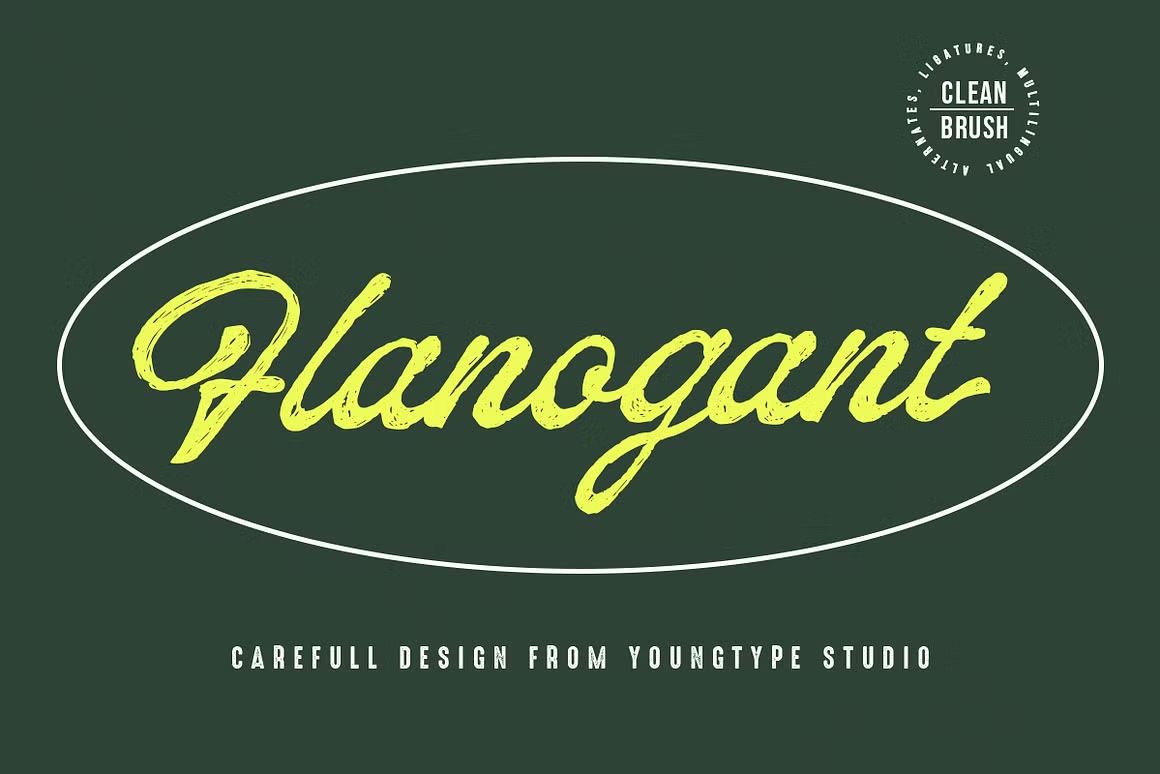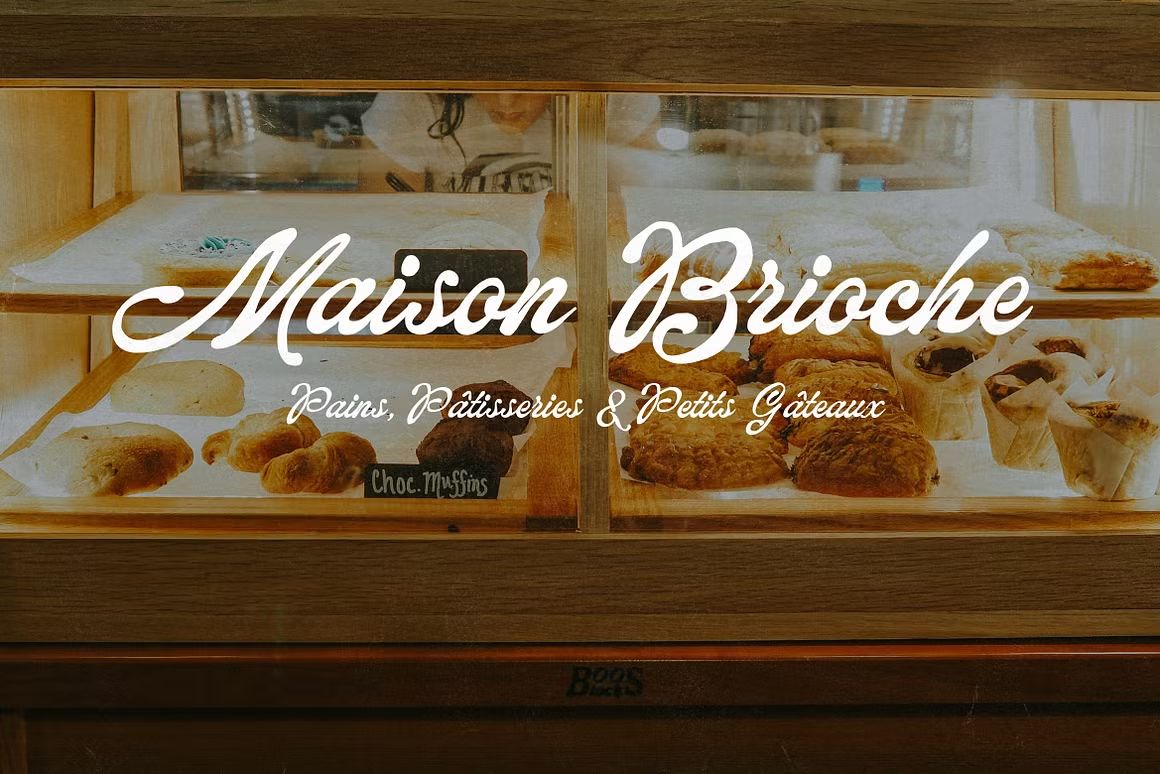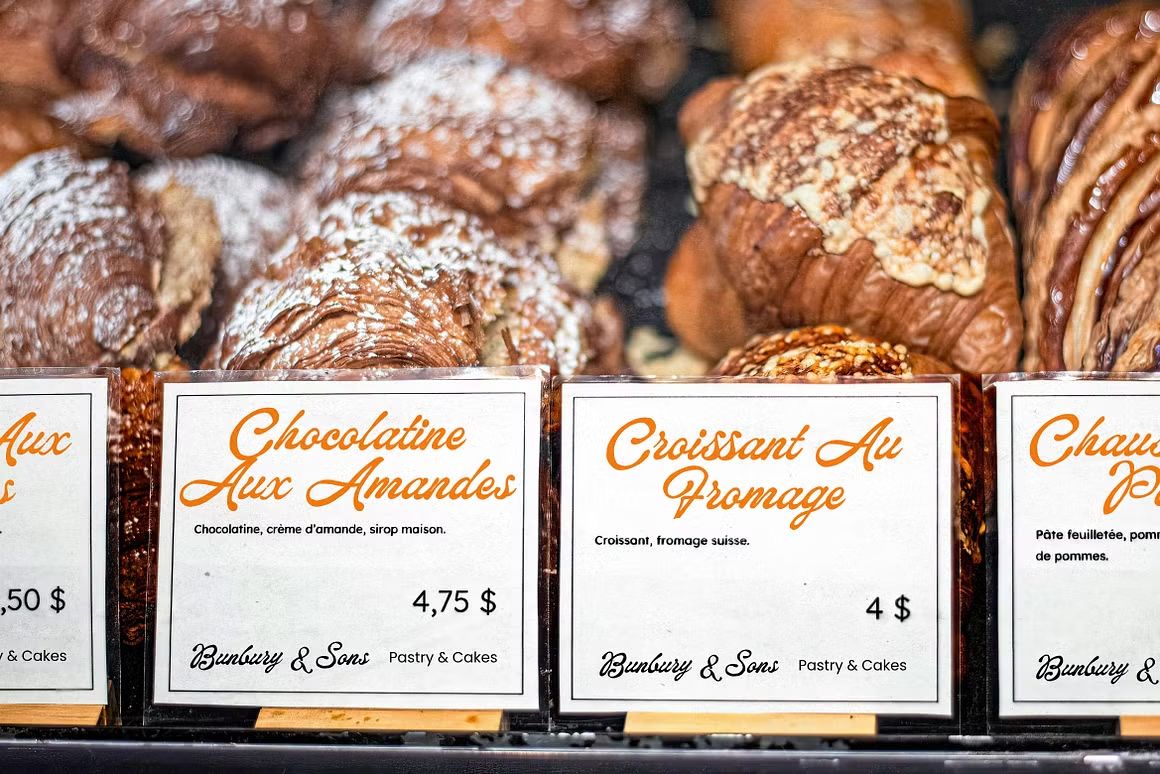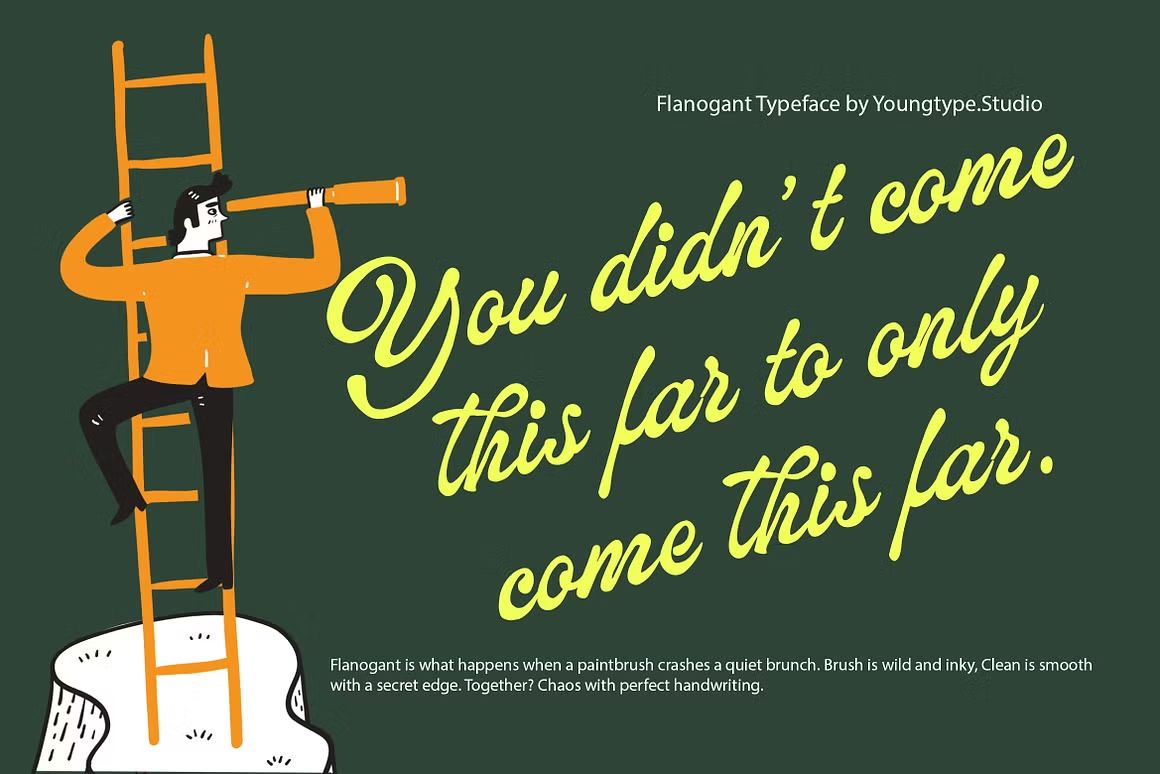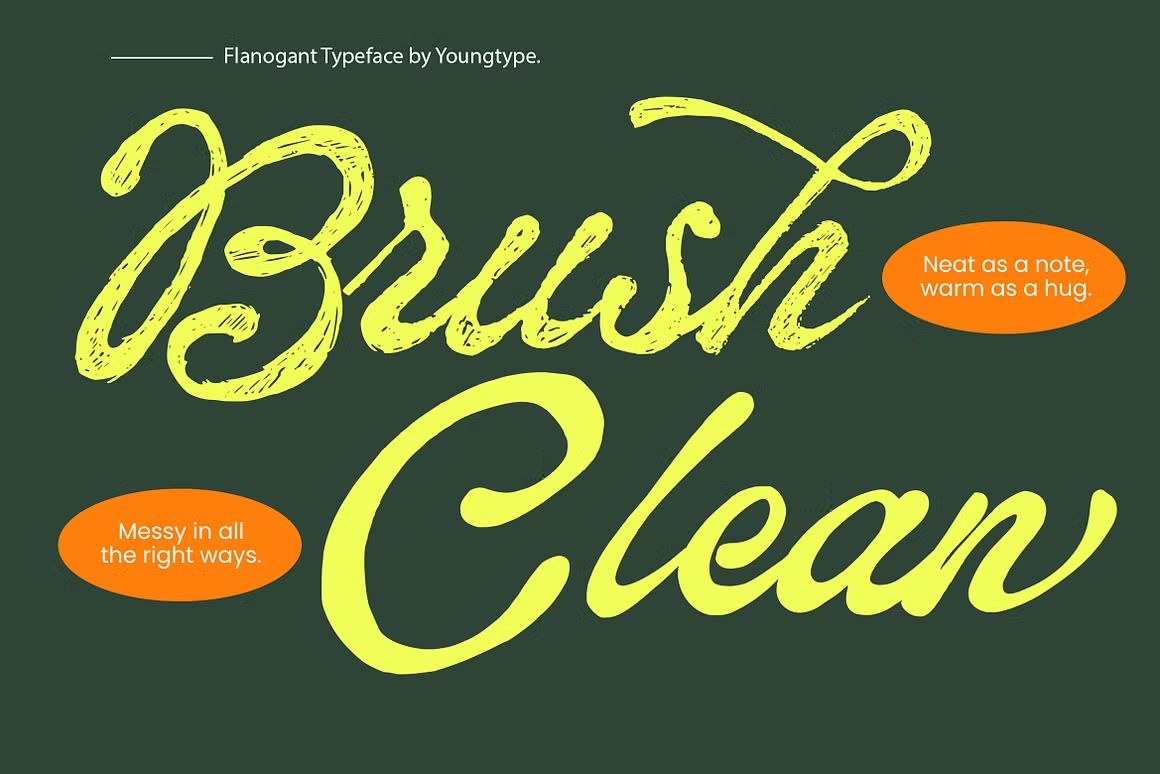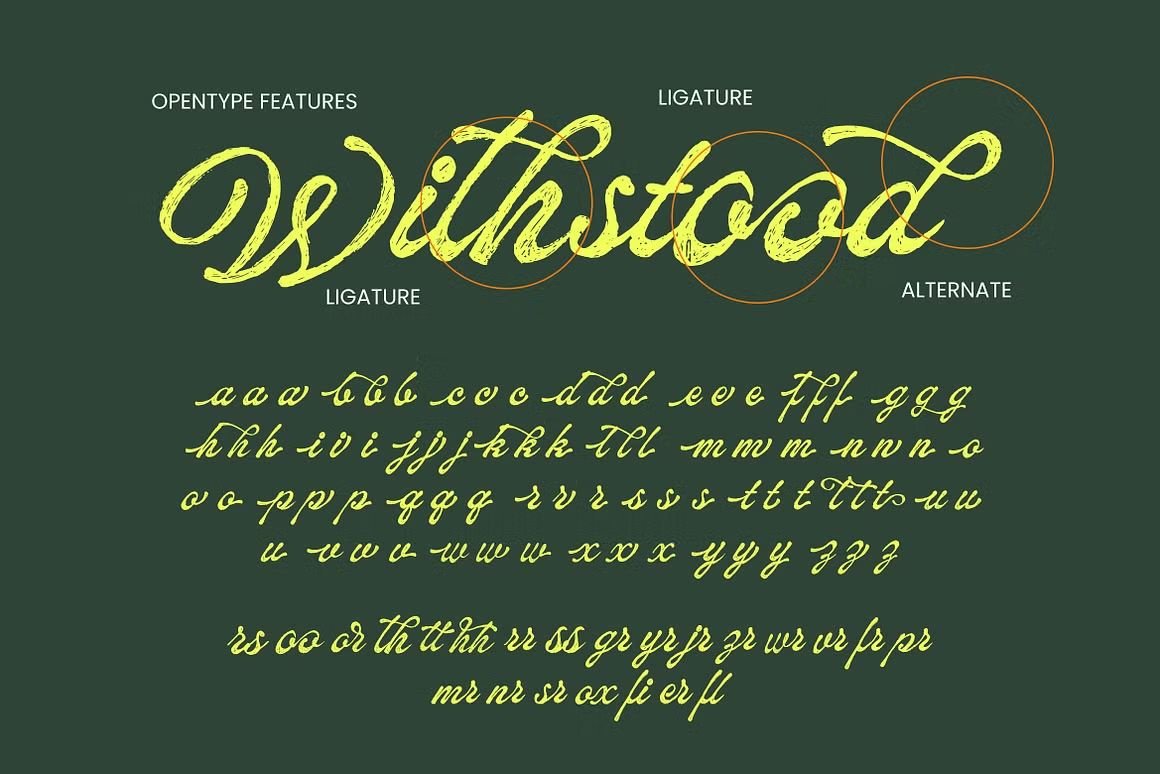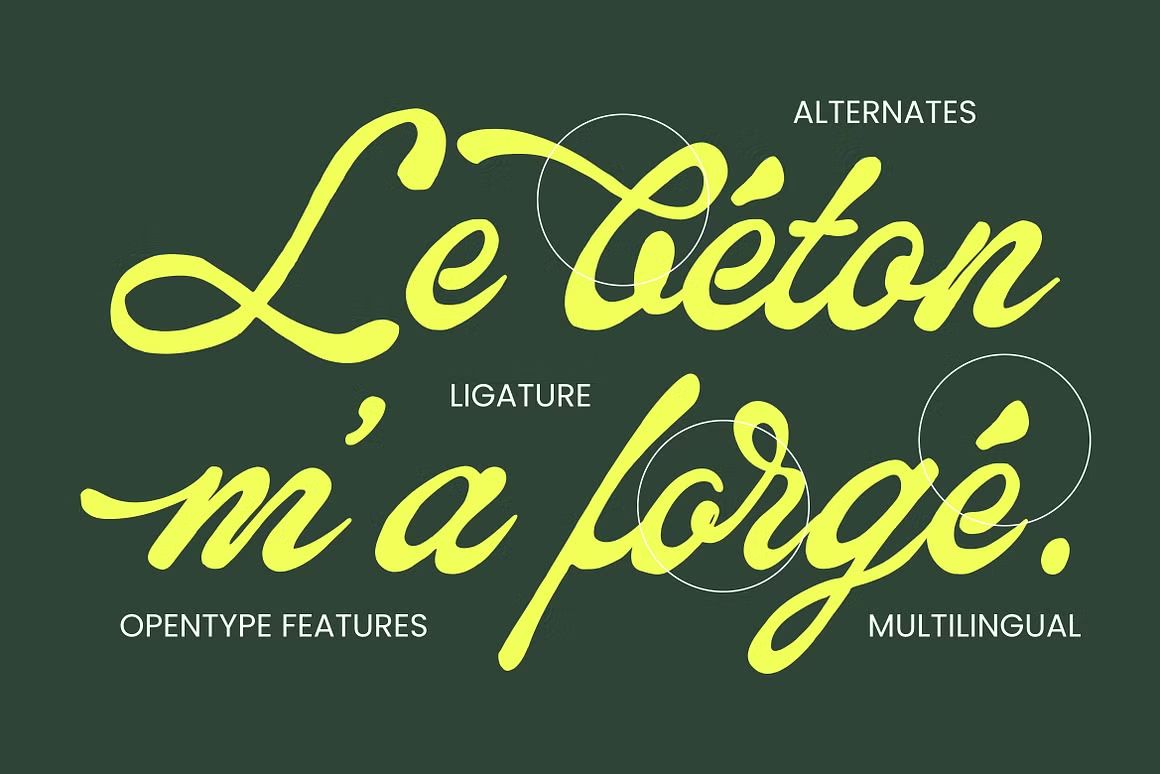
Flanogant – Script Font
Flanogant adalah font script elegan dan halus, cocok untuk wedding, logo, dan desain mewah. Tersedia dalam format OTF/TTF/WOFF, siap digunakan di berbagai platform desain.
Flanogant adalah font script bergaya elegan dengan garis halus dan lekukan dinamis yang menyerupai tulisan tangan mewah. Font ini sangat cocok untuk proyek desain seperti undangan pernikahan, logo brand premium, kemasan produk, kutipan estetik, dan media sosial. Karakteristiknya yang feminin, anggun, dan modern menjadikan Flanogant pilihan ideal untuk menambah kesan eksklusif dan artistik.
• Gaya script elegan dengan alur tulisan yang halus
• Cocok untuk wedding, branding, dan desain feminin
• Tersedia huruf besar, kecil, angka, simbol, dan ligatur